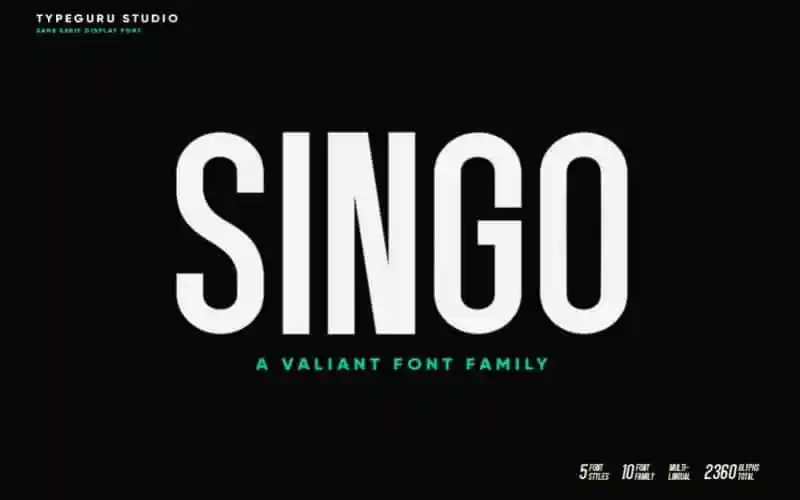
Singo Sans Serif Font – Download Grátis
A fonte Singo Sans Serif é uma escolha perfeita para criar design de alta qualidade em grandes tamanhos. Por ser uma fonte sans serif densa e robusta, criada pelo designer typeguru, ela oferece um equilíbrio ideal entre elegância e força, tornando-se ótima para headlines vigorosos ou qualquer tipo de aplicação visual onde seja necessária uma presença dominante. Seja em menuções titulares, embalagens, ou qualquer outro uso que exige uma forte impressão, a fonte Singo garantirá um resultado profissional e impactante. O pacote básico inclui letras A-Z, números 0-9 e caracteres especiais limitados conforme mostrado nas imagens de lista. Essa combinação completa de caracteres torna a fonte ideal para qualquer aplicação que exige uma variedade rica de símbolos e letras. Além disso, a sua densidade permite-lhe usar um tamanho maior da letra sem perder nitidez ou força visual. A fonte Singo é perfeitamente adaptável ao design de qualquer produto, seja ele impresso em embalagens ou exibido como texto digital na internet. Com seu estilo robusto e moderno, ela pode ajudá-lo a destacar sua marca e transmitir sua mensagem com clareza e destreza. Seja você um designer gráfico atento aos detalhes ou uma empresa que busca transformar seus produtos em verdadeiros ícones do mercado, a fonte Singo Sans Serif oferece uma ferramenta poderosa para criar designs memoráveis e profissionais.